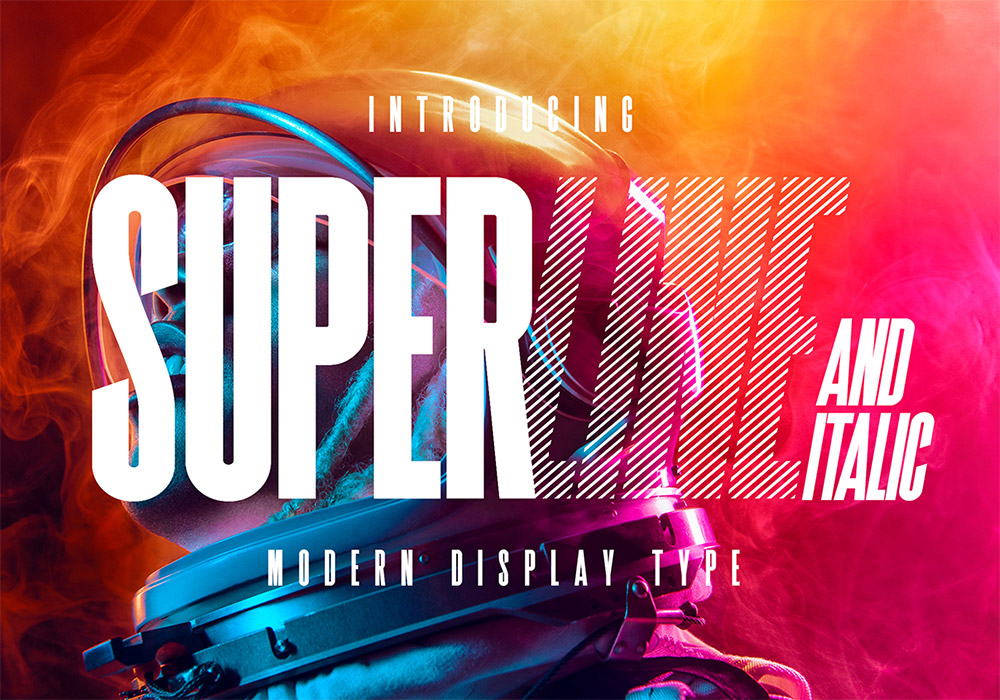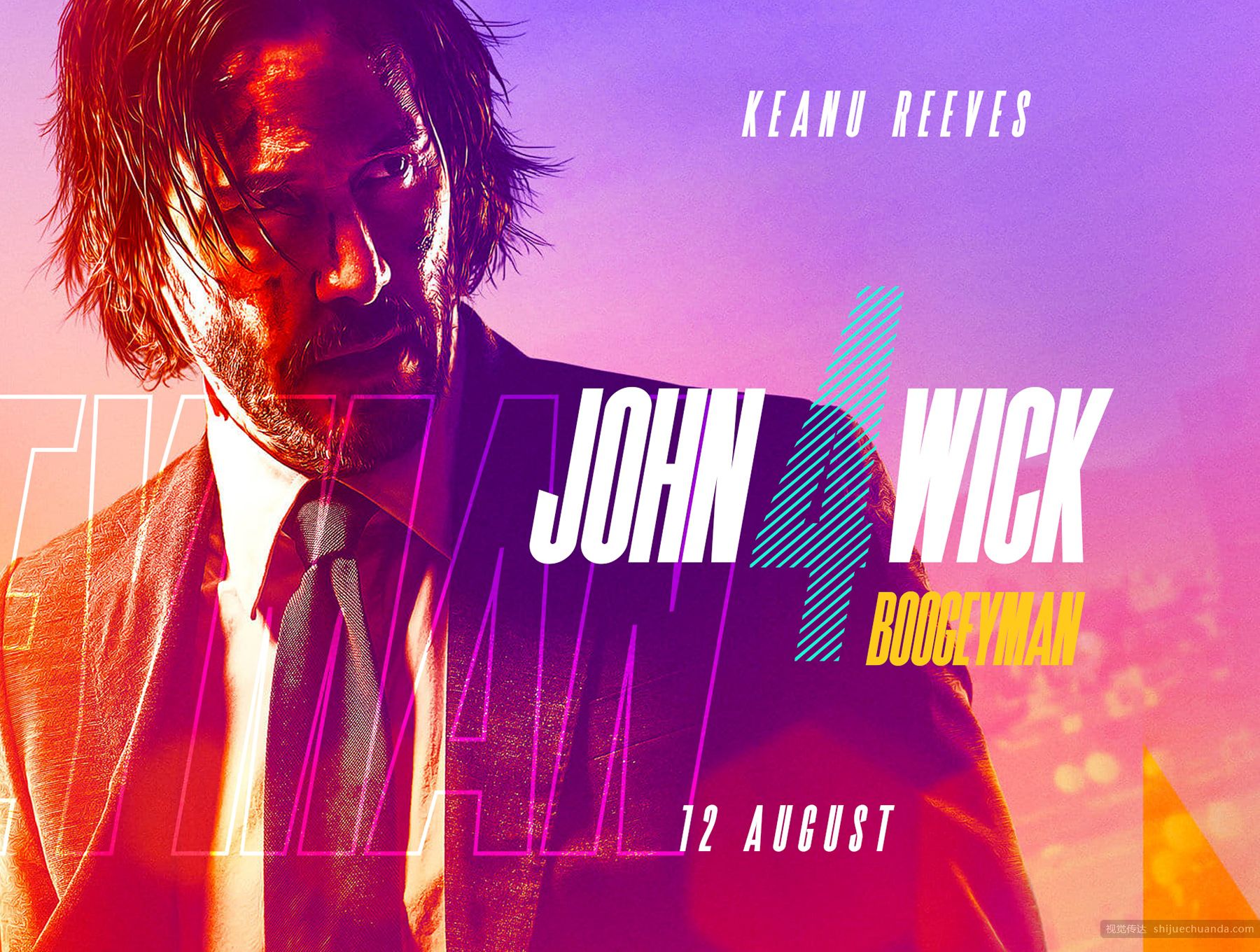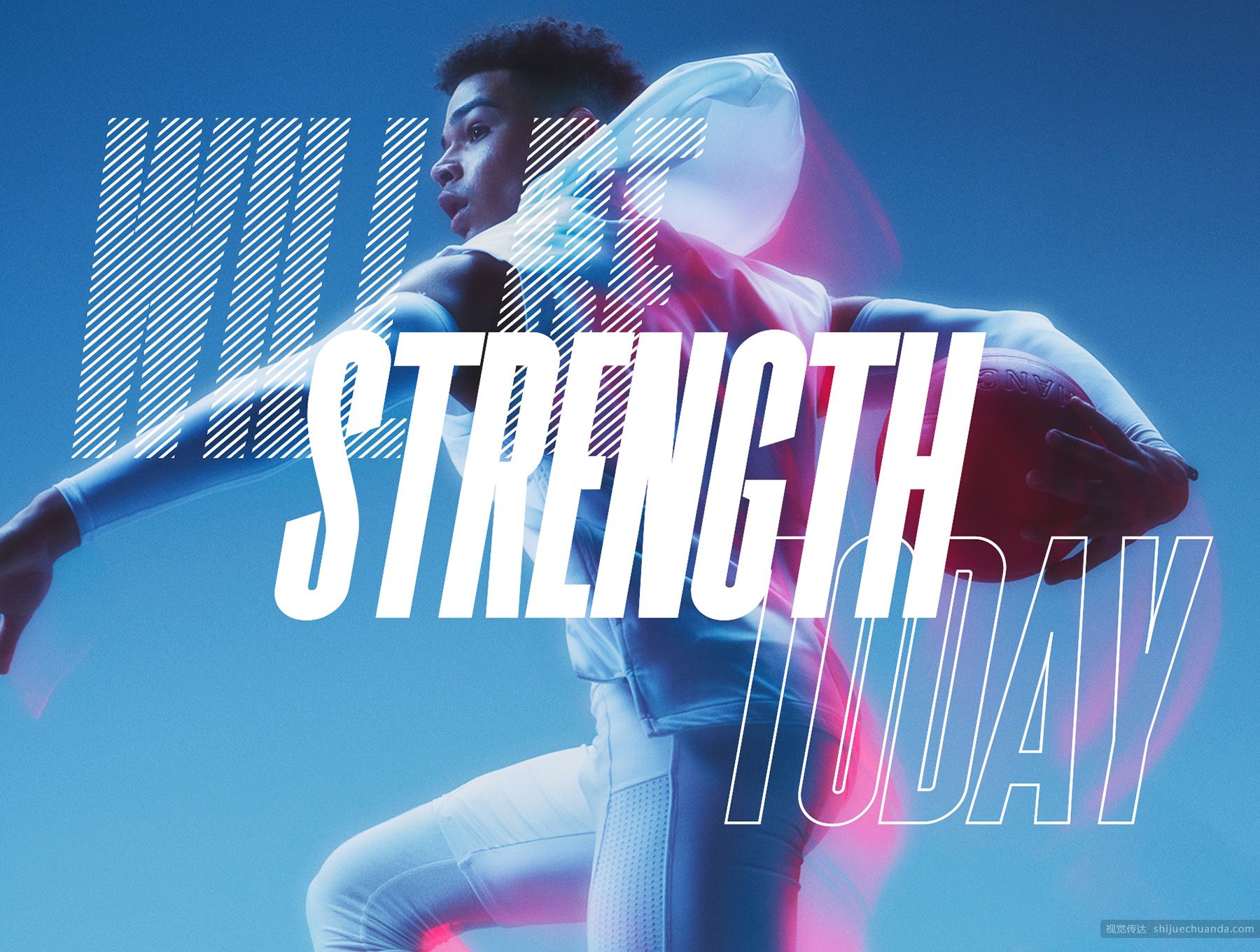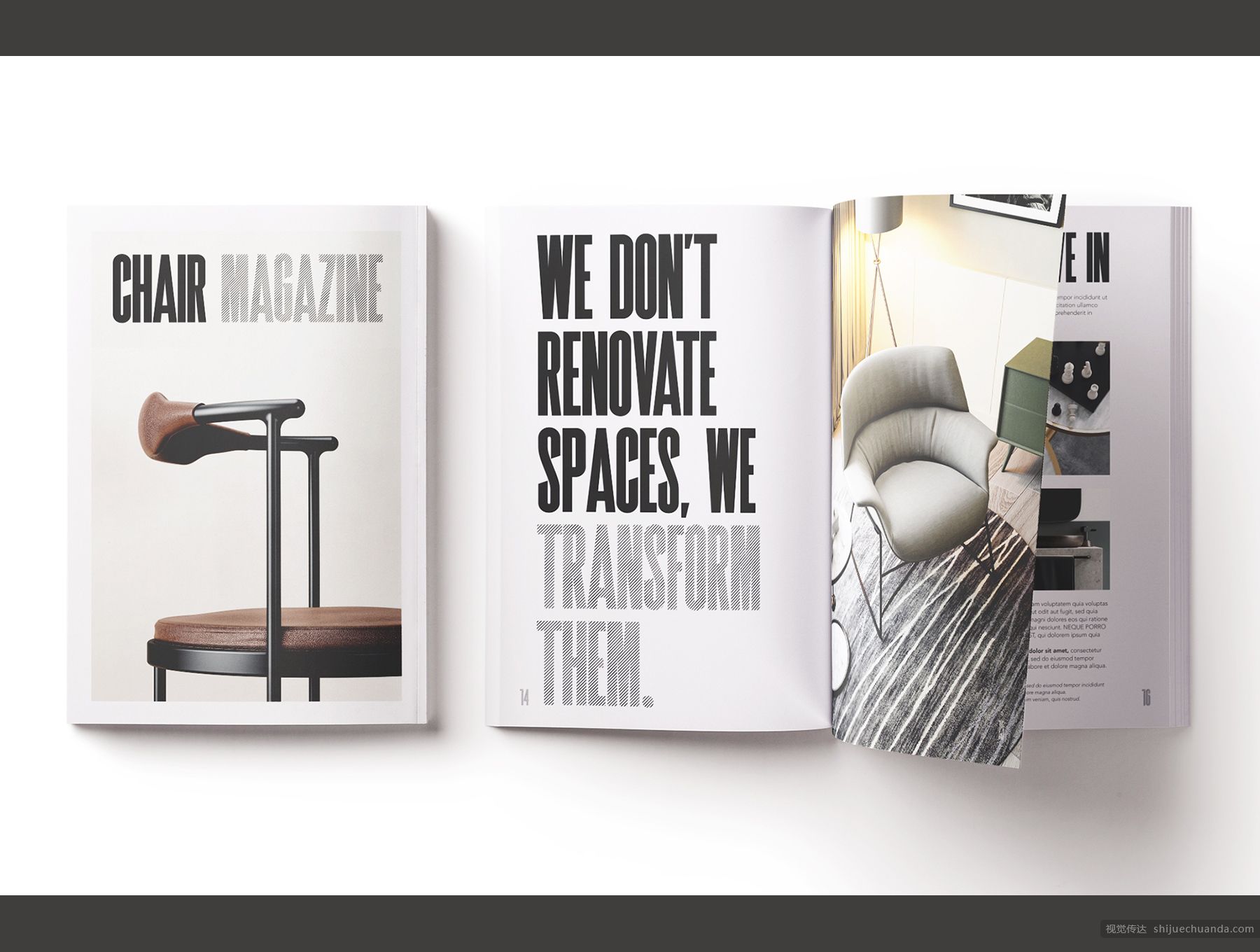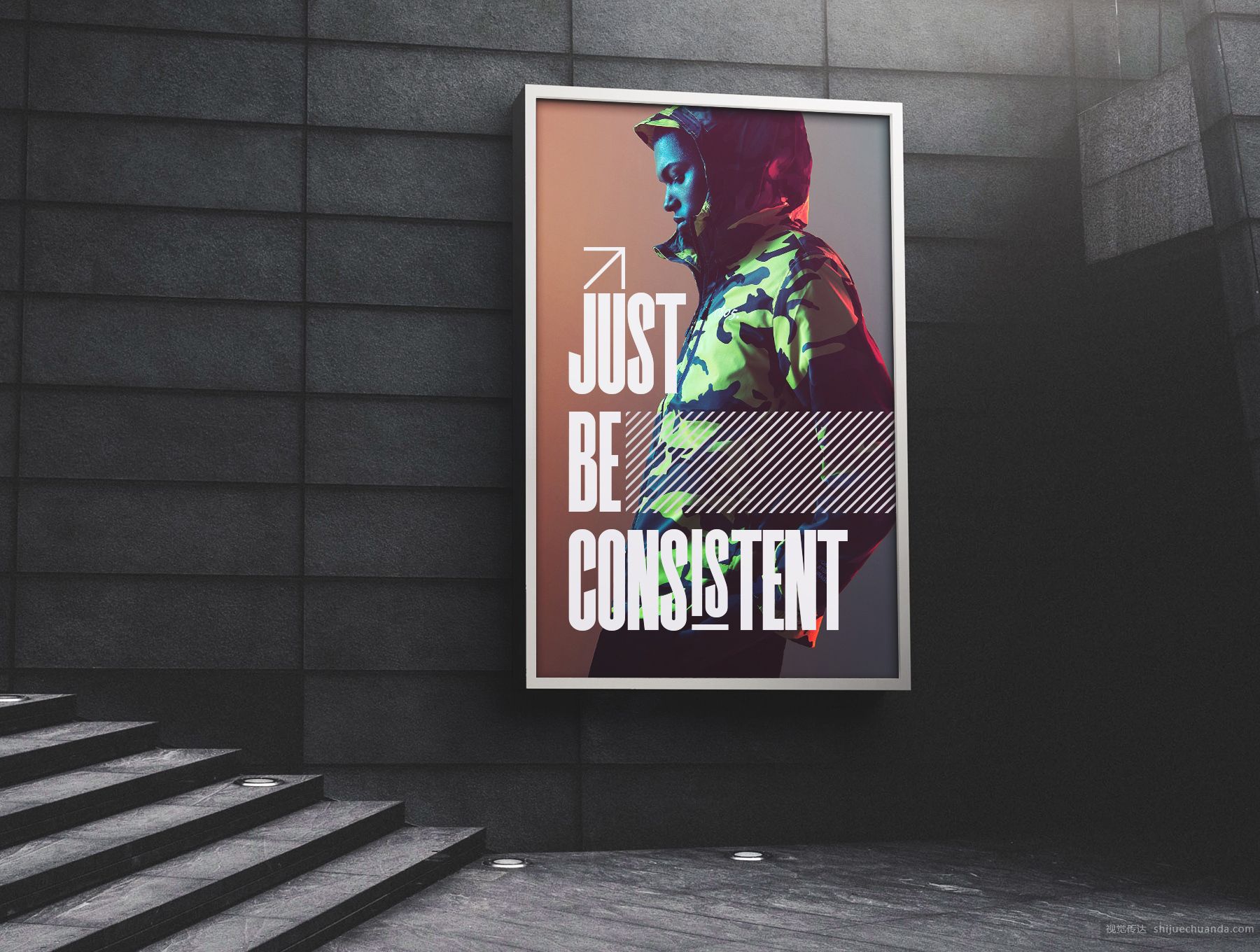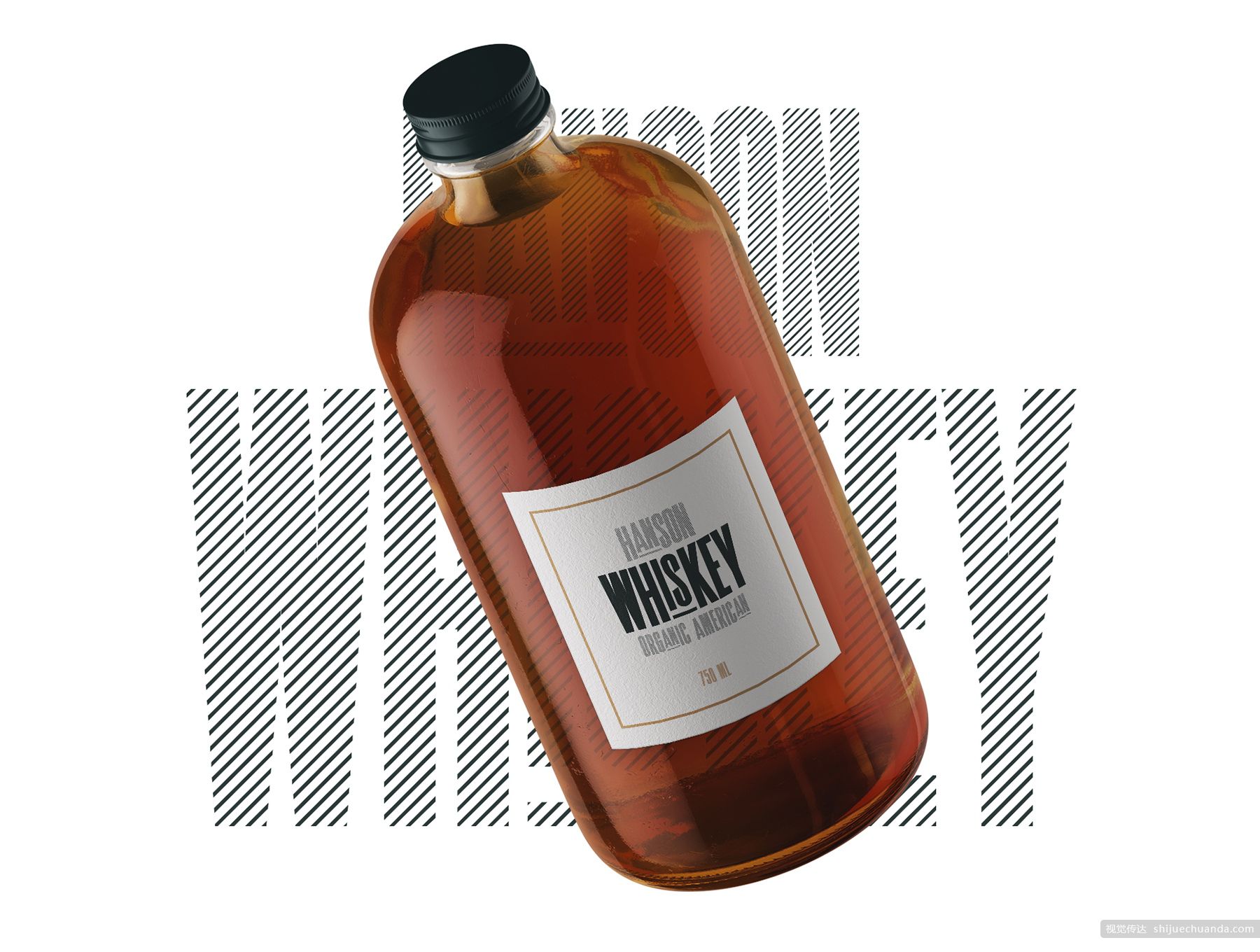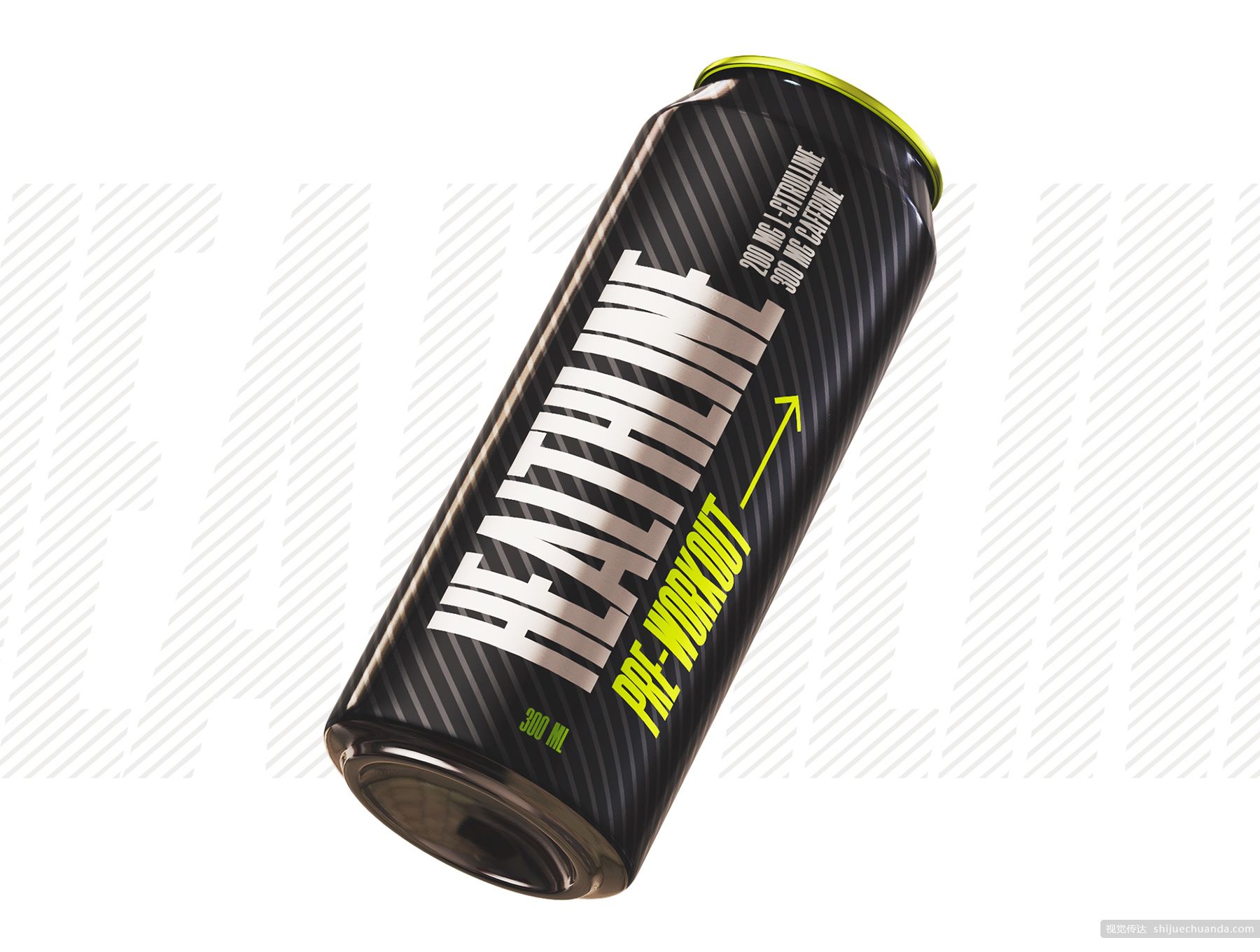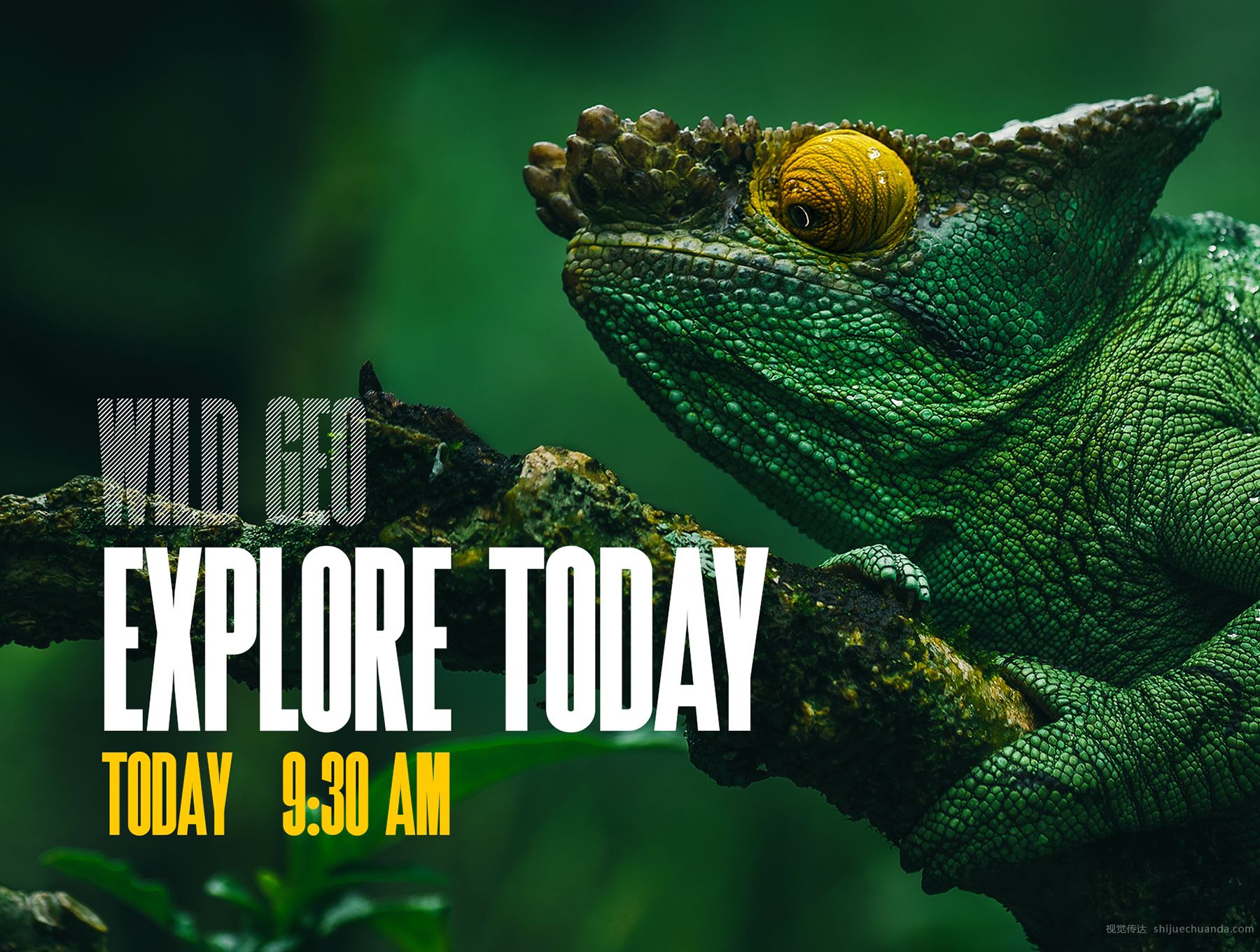
三种风格的醒目现代显示字体 SuperLine Display Typeface
SuperLine是一种现代的全大写显示字体,TTF和WOFF格式,专为现代设计风格和应用而开发,提供三种风格:规则,内衬和轮廓。SuperLine非常适合品牌项目,醒目的海报以及作为Web或应用程序开发的独特显示字体,是您的理想之选。包括扩展形状背景。这些形状旨在补充SuperLine字体中的角度,非常适合用作遮罩,图像覆盖或纯色背景填充。它们以Illustrator(ai和eps)矢量格式提供。